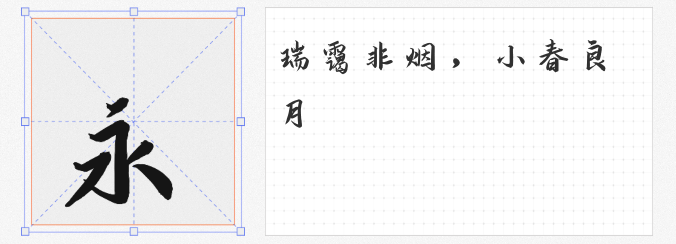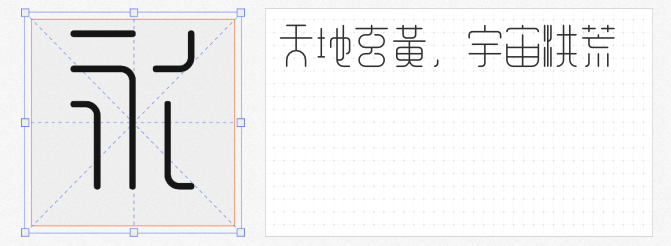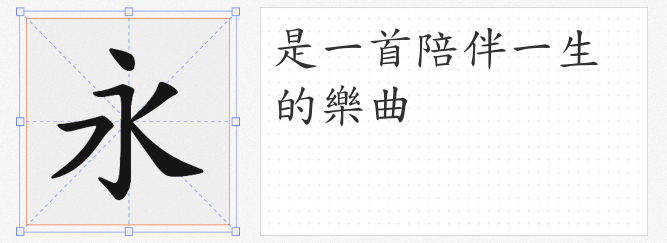
在平面设计中,书法字体既能传递文化韵味,又能赋予作品独特的视觉张力。以下四款免费商用书法字体,兼顾传统笔意与现代设计需求,适用场景广泛,值得设计师收藏备用。
1. 寒蝉书体·春秋 春风
基于开源字体「演示春风楷」拓展而成的寒蝉书体·春秋 春风,完美融合了两种字体的风格精髓。其笔画挺拔而不失柔美,字形结构均衡,既保留了楷书的端庄骨架,又通过细节优化提升了现代感。这款字体支持简体中文,并调整了西文字符与数字的排版适配性,尤其适合需要中西文混排的设计场景。无论是品牌包装、书籍封面,还是国风海报与艺术展览物料,其刚柔相济的笔触都能为作品增添文化底蕴。
2. 全字库正楷体
作为台湾CNS11643中文标准交换码计划的产物,全字库正楷体自1980年起便承担着统一中文内码交换的重任。这款字体以标准楷书为基底,笔画工整规范,字符集覆盖简体与繁体,且完全兼容商用场景。其设计虽不追求强烈个性,但中正平和的气质使其成为政府公文、教育教材、企业年报等正式场合的可靠选择。对于需要避免版权风险的大型项目,全字库正楷体的权威背景与开放许可(依《台湾政府资料开放授权条款》)更是一重保障。
3. 余繁新语 Regular
以MIT协议开源的余繁新语,通过简化小篆结构创造出极具辨识度的现代书法风格。其笔画粗细对比强烈,字形略带几何化处理,既保留了篆书的古朴韵味,又适配了当代视觉审美。这款字体尤其适合需要强烈视觉冲击力的场景,如电商海报主标题、品牌标志设计、文化展陈空间导视系统等。值得注意的是,其繁体字库支持需在设计时注意字符适配,但正是这种“不完美”的拙朴感,赋予了作品独特的手工温度。
4. 演示悠然小楷
由keynote研究所与秋叶PPT联合发布的演示悠然小楷,以“停而不断、笔断意连”的笔触,在楷书的规整与行书的流畅间找到了平衡点。其笔画力度分布均衡,字间距自然宽松,即便作为长段落正文使用,也能保证阅读的舒适性。这款字体既可驾驭文艺风书籍装帧、茶饮品牌包装等传统场景,又能通过灵动的笔画细节为科技产品海报、现代艺术展览增添一抹人文气息。